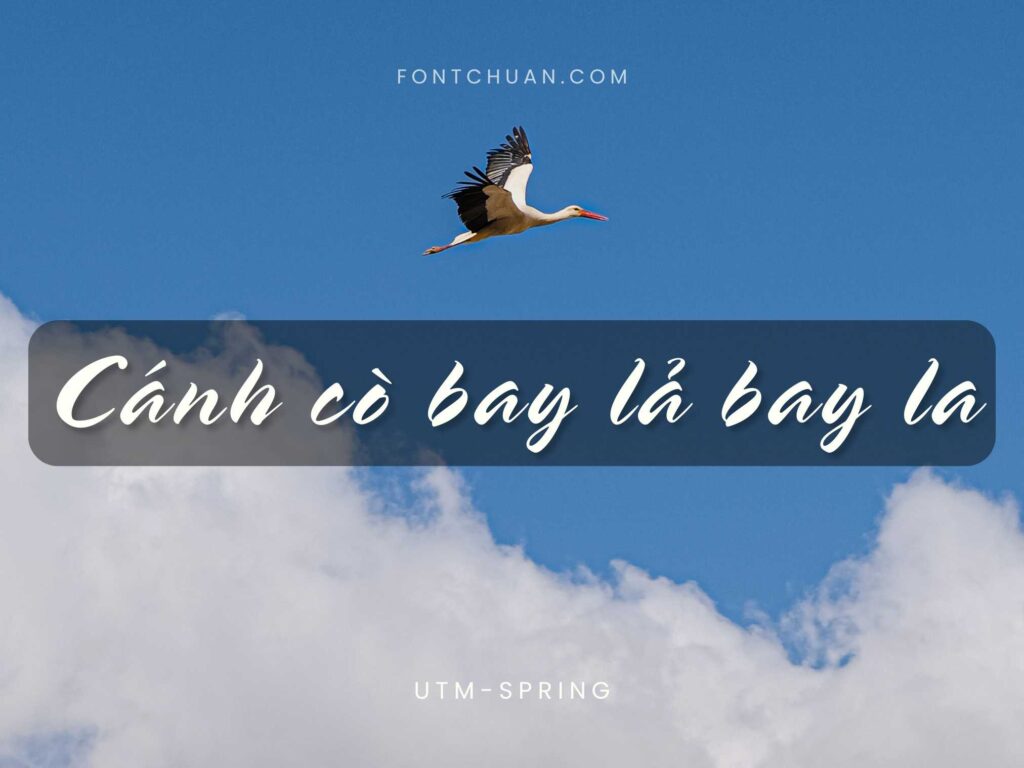
UTM Spring là một Font chữ thư pháp trang trí độc đáo, mang phong cách mềm mại và uyển chuyển.. Được phát triển bởi Công ty TNHH Vitoen, font này thể hiện sự sáng tạo và tinh tế trong thiết kế, tạo điểm nhấn đặc biệt cho các dự án cần sự nổi bật và thu hút. Với thiết kế độc đáo, UTM Spring thường được sử dụng trong các dự án như thiệp mời, tiêu đề, poster và các ấn phẩm nghệ thuật khác.
Font này đã được Việt hóa bởi Thiên Minh, đảm bảo hỗ trợ đầy đủ các dấu và ký tự tiếng Việt, mang lại trải nghiệm sử dụng hoàn chỉnh cho người dùng. Ngoài tiếng Việt, UTM Spring còn hỗ trợ nhiều ngôn ngữ khác, mở rộng khả năng ứng dụng trong các thiết kế quốc tế. Thành viên của Font Chuẩn đã sưu tầm và giới thiệu UTM Spring đến cộng đồng thiết kế, giúp họ có thêm lựa chọn cho các dự án sáng tạo. Với sự kết hợp giữa tính thẩm mỹ và khả năng ứng dụng cao, font này phù hợp cho các thiết kế thiệp cưới, tiêu đề sách, poster và các ấn phẩm nghệ thuật khác.